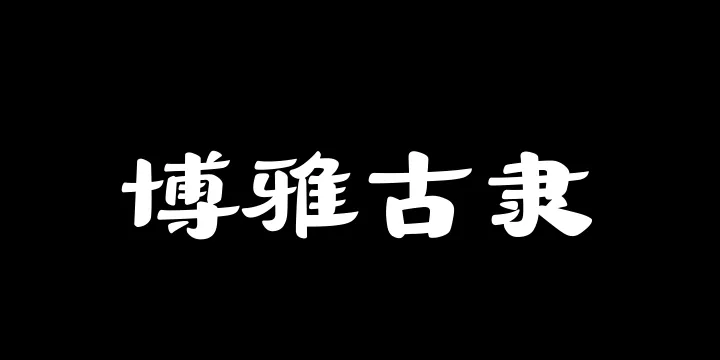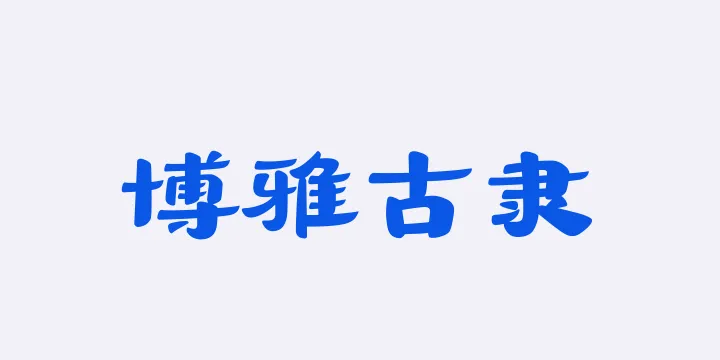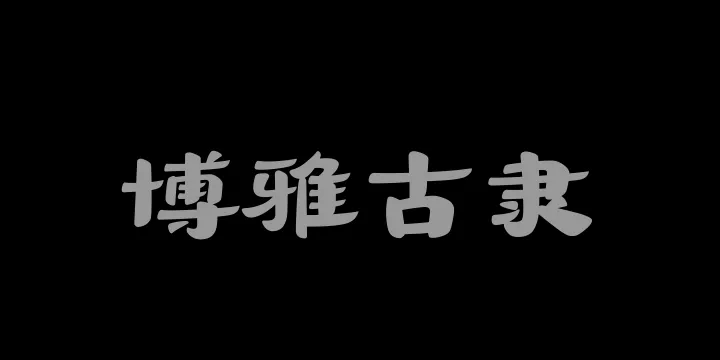
字体全名: 山海博雅古隶W
字体简介: 山海博雅古隶,是一款全新的字体,包含汉字9169个,符号200+个,是一款带有隶书韵味的国潮风字体。该字体字形优美文雅,禅韵内敛,书法的运笔走势蕴含其中,流畅自然,蕴含东方审美韵味,尽显优雅从容,秀雅清新。整体以隶书为骨,字形扁方,取正势,重心平稳,结体紧实,笔画铿锵有力。该字体适合用于传统文化相关的使用场景,如时令节气、节日庆典、民俗特产等,也适用于新中式风格的品牌,彰显中华气韵。